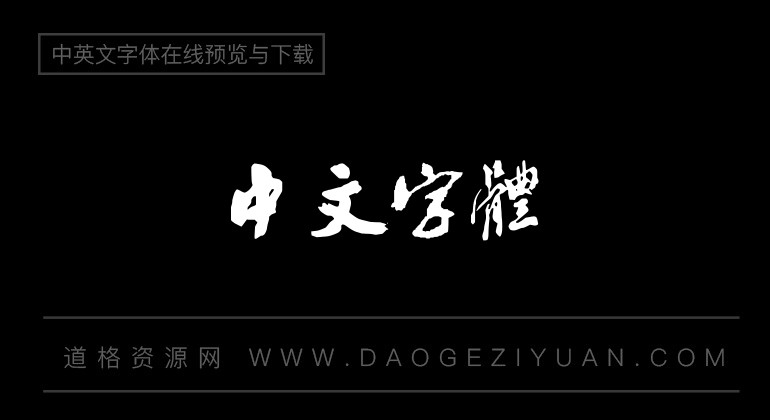
沙孟海书法
沙孟海书法是一种以沙漠风格为特色的书法字体。它的特点是笔画粗犷,笔画灵活,笔锋有力,节奏有致,极具质感,具有浓郁的沙漠气息,极具视觉冲击力。沙孟海书法以沙漠风格为特色,以沙漠中的风沙为灵感,结合传统书法的笔画技法,创造出一种独具特色的书法字体。
沙孟海书法是一款非常不错的手写艺术字体,具有很好的视觉感,适合于文化类的宣传设计、商业类品牌的广告和产品包装设计以及个性化文字排版等较多场景。